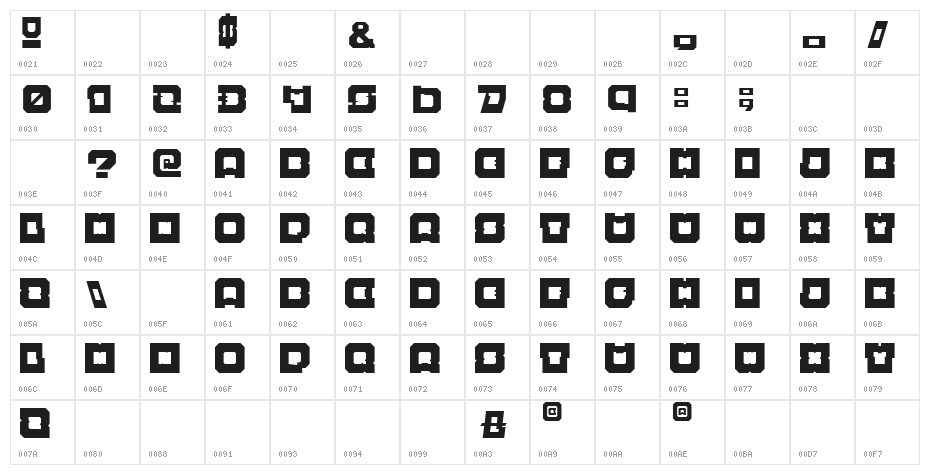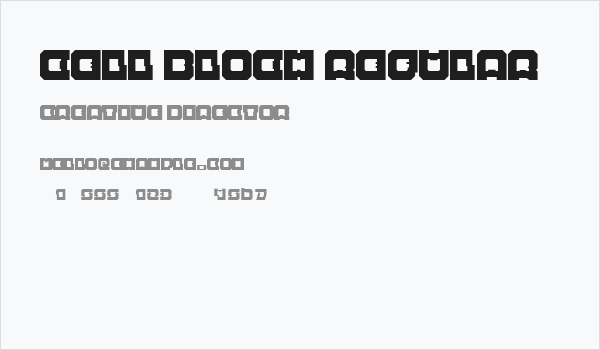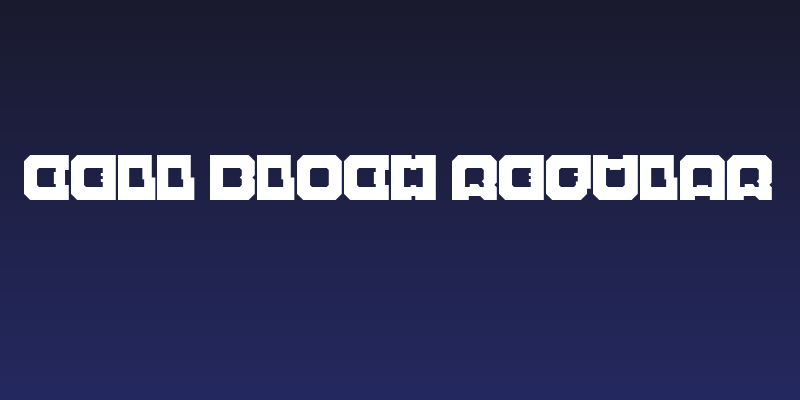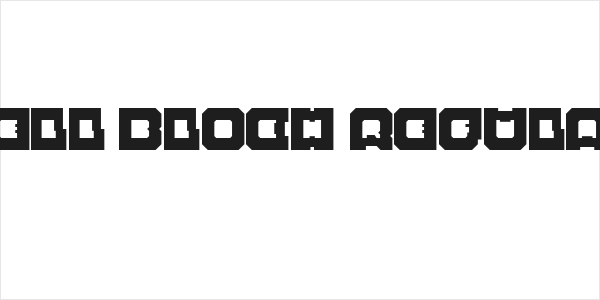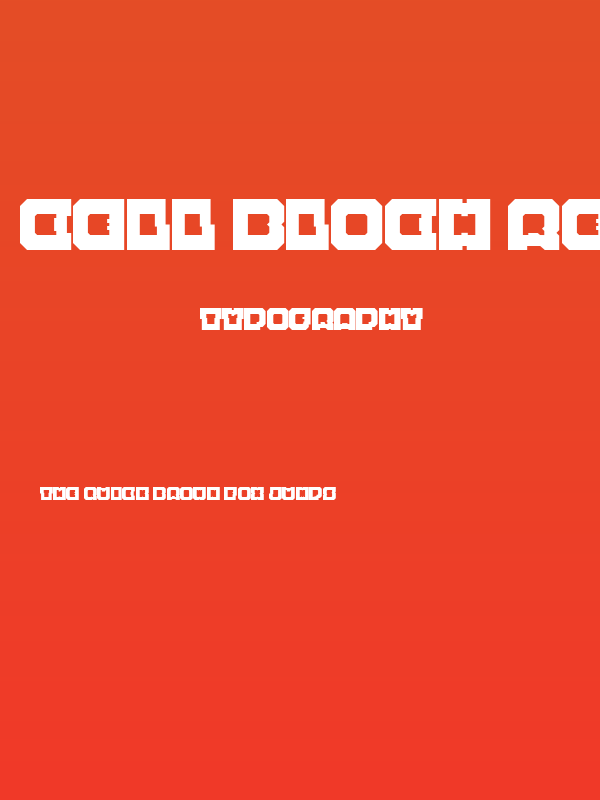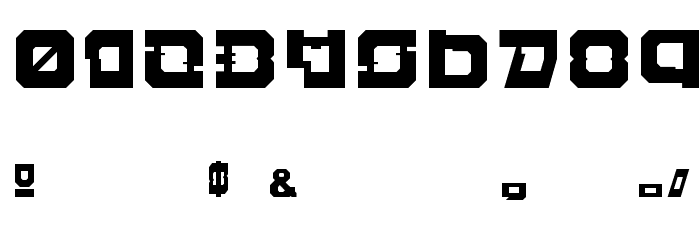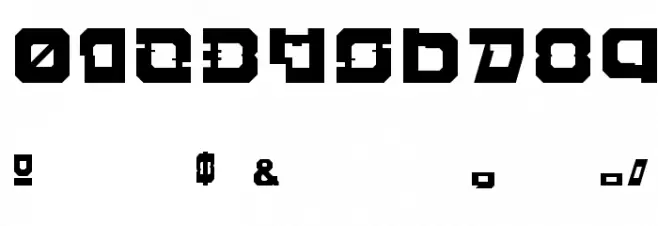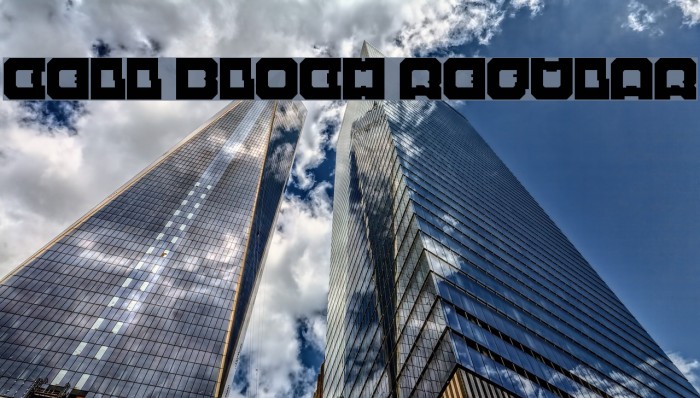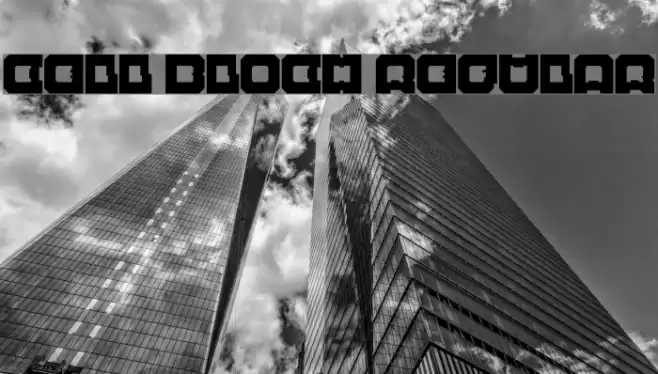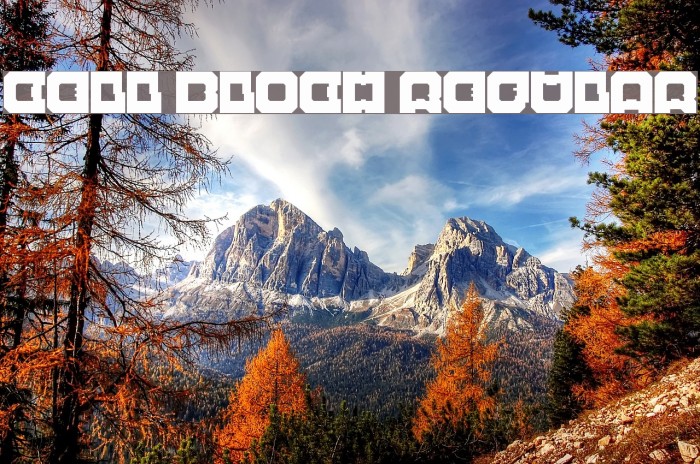
Cell Bloch Regular Font
| Proiecte propuse | Ideal for use in branding, posters, headlines, and any project requiring a modern, industrial aesthetic. |